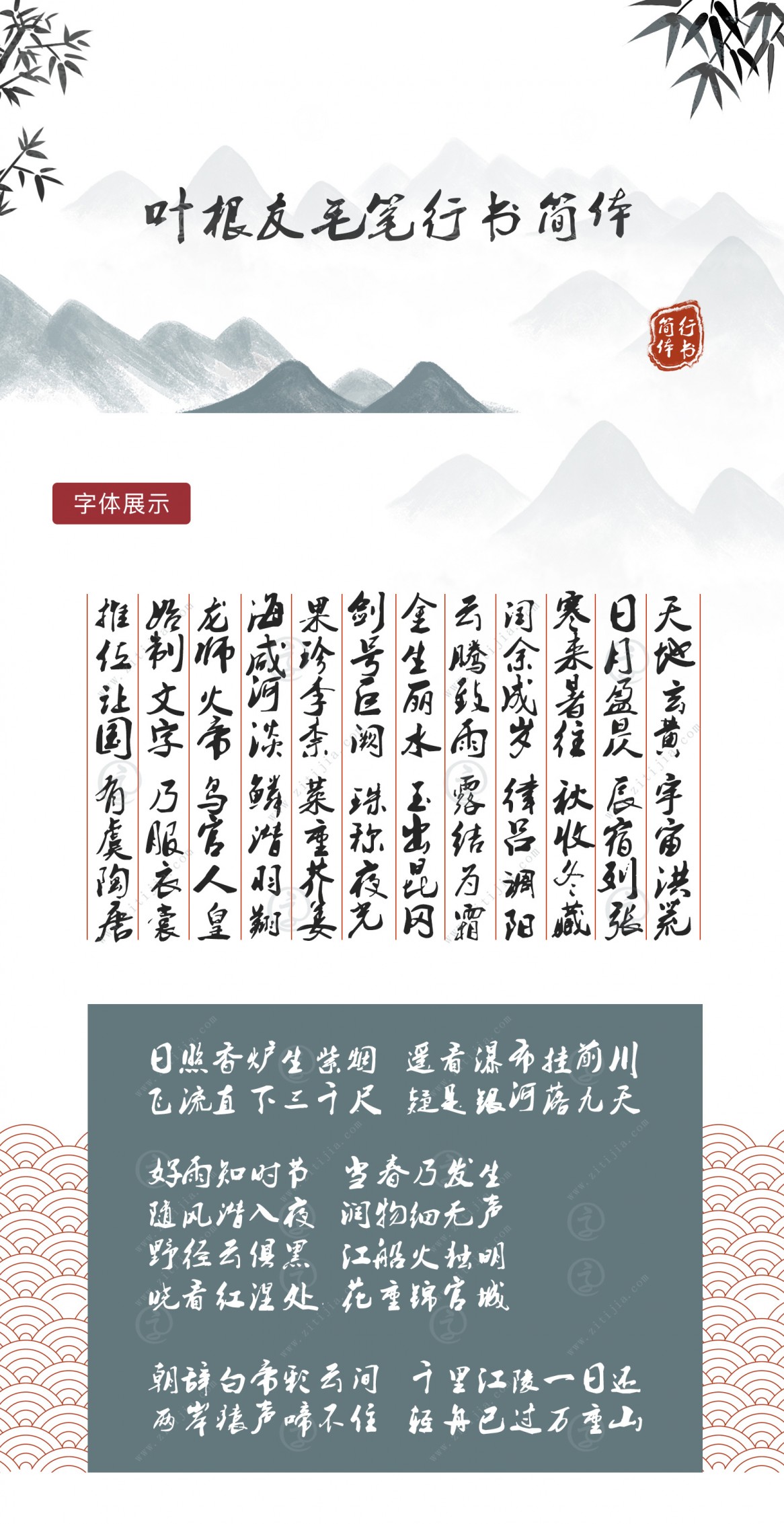
葉根友毛筆行書(shū)簡(jiǎn)體2.1
字體作者:葉根友
創(chuàng)作年代:2007年
字體字?jǐn)?shù):6763個(gè)中文漢字以及其他英文字母和阿拉伯?dāng)?shù)字
字體介紹
這是一款葉根友字體系列最受歡迎的字體之一,葉根友毛筆行書(shū)簡(jiǎn)體是具有獨(dú)特風(fēng)格的字體,筆意取自米芾書(shū)法風(fēng)格,大氣而又自然流暢是這款字體的主要風(fēng)格。廣泛應(yīng)用于社會(huì)各界的廣告招牌、影視作品以及游戲應(yīng)用等。
一款2007年創(chuàng)意的字體,筆畫(huà)風(fēng)格大氣流暢,書(shū)寫(xiě)自然,是一種純手寫(xiě)字體的經(jīng)典之作,之前第一版顯示葉根友毛筆行簡(jiǎn)體“明”字錯(cuò)誤,在2011年時(shí)已經(jīng)更正該錯(cuò)誤,請(qǐng)各用戶注意甄別,如善未替換的用戶請(qǐng)重新下載該升級(jí)版葉根友毛筆行書(shū)字體,2010年2月4日升級(jí)完成該版本2.1版本升級(jí),重新書(shū)寫(xiě)了英文26個(gè)大小寫(xiě)字母和數(shù)字以及漢字的筆畫(huà)信息優(yōu)化,調(diào)整了字?jǐn)?shù)上下距離、大小等。
創(chuàng)作記事
2007年8月,初創(chuàng)該字體字稿
2007年11月,發(fā)行葉根友毛筆行書(shū)1.0版本
2010年2月,重新調(diào)整該字體中字與字的比例、大小位置等更新升級(jí)
2020年5月,重新調(diào)整部分字型以及修正蘋(píng)果電腦系統(tǒng)不兼容問(wèn)題